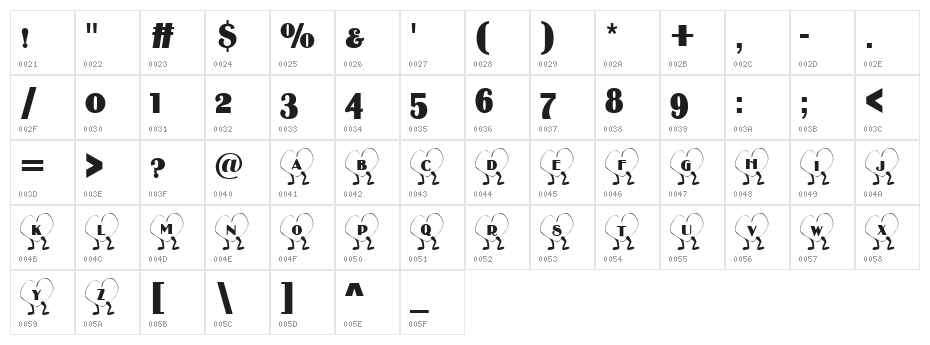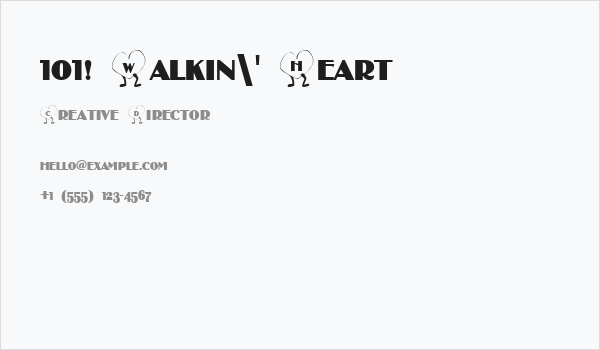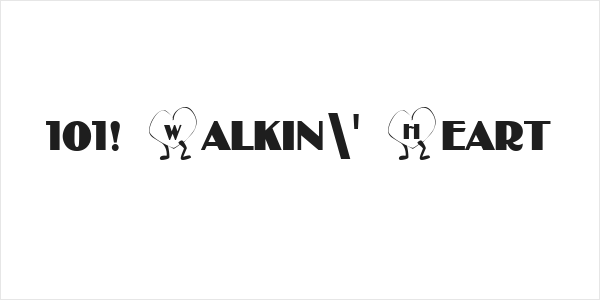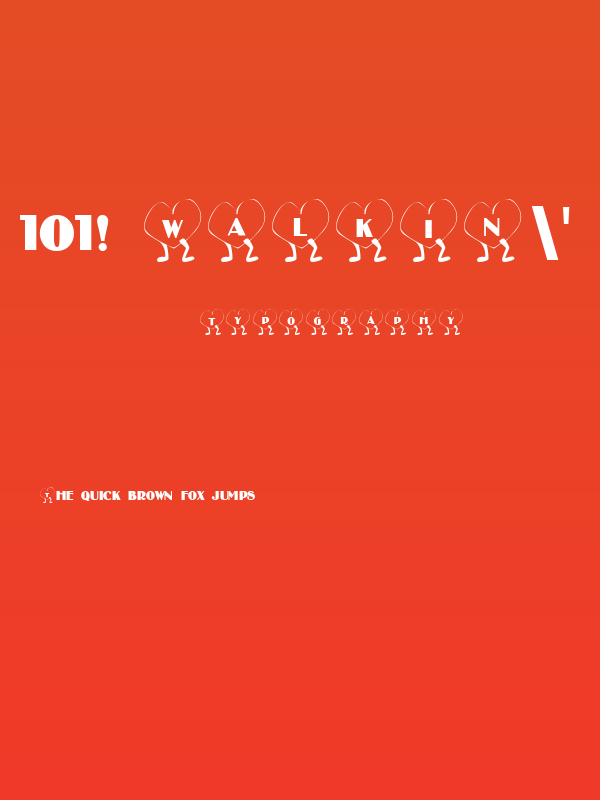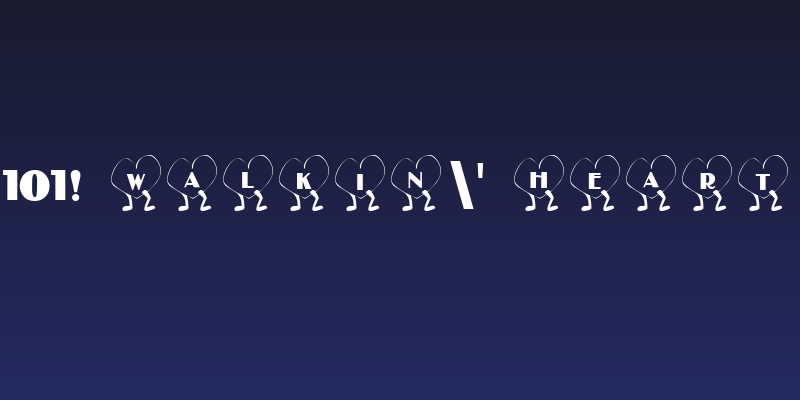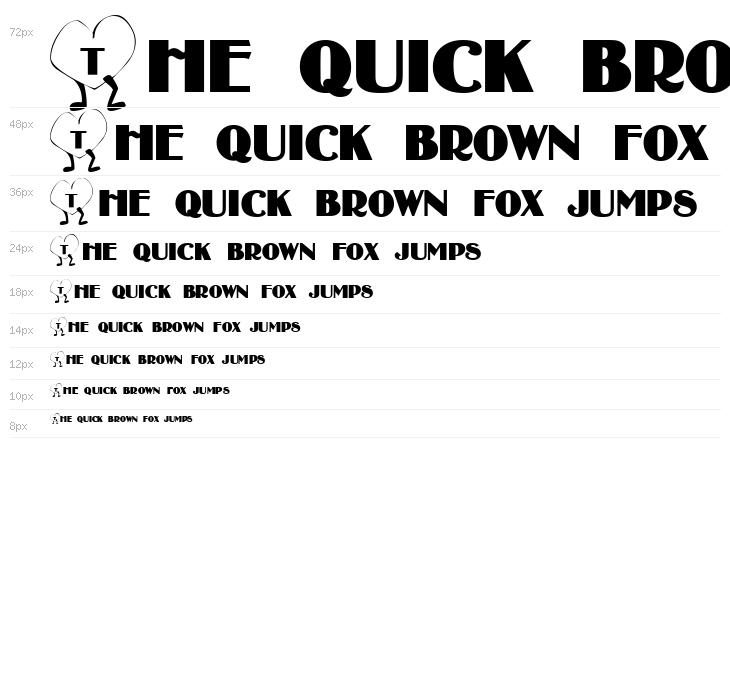
101! Walkin' Heart Font
| Stile generale | Playful, Whimsical |
| Caso d'uso | Logos, Posters, Invitations |
| Progetti proposti | Ideal for children's books, playful branding, Valentine's Day promotions, and greeting cards. |